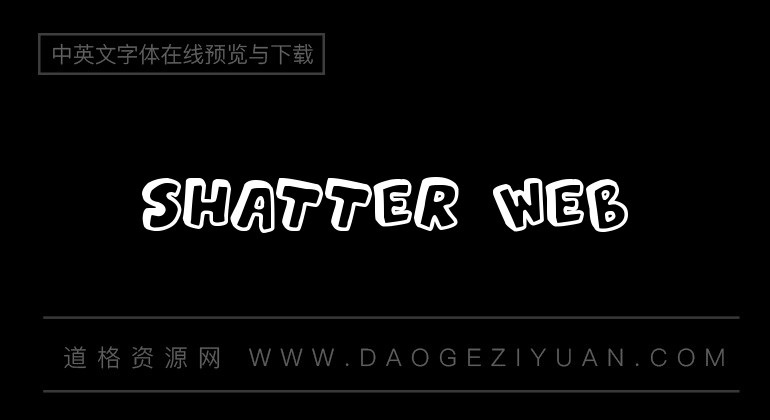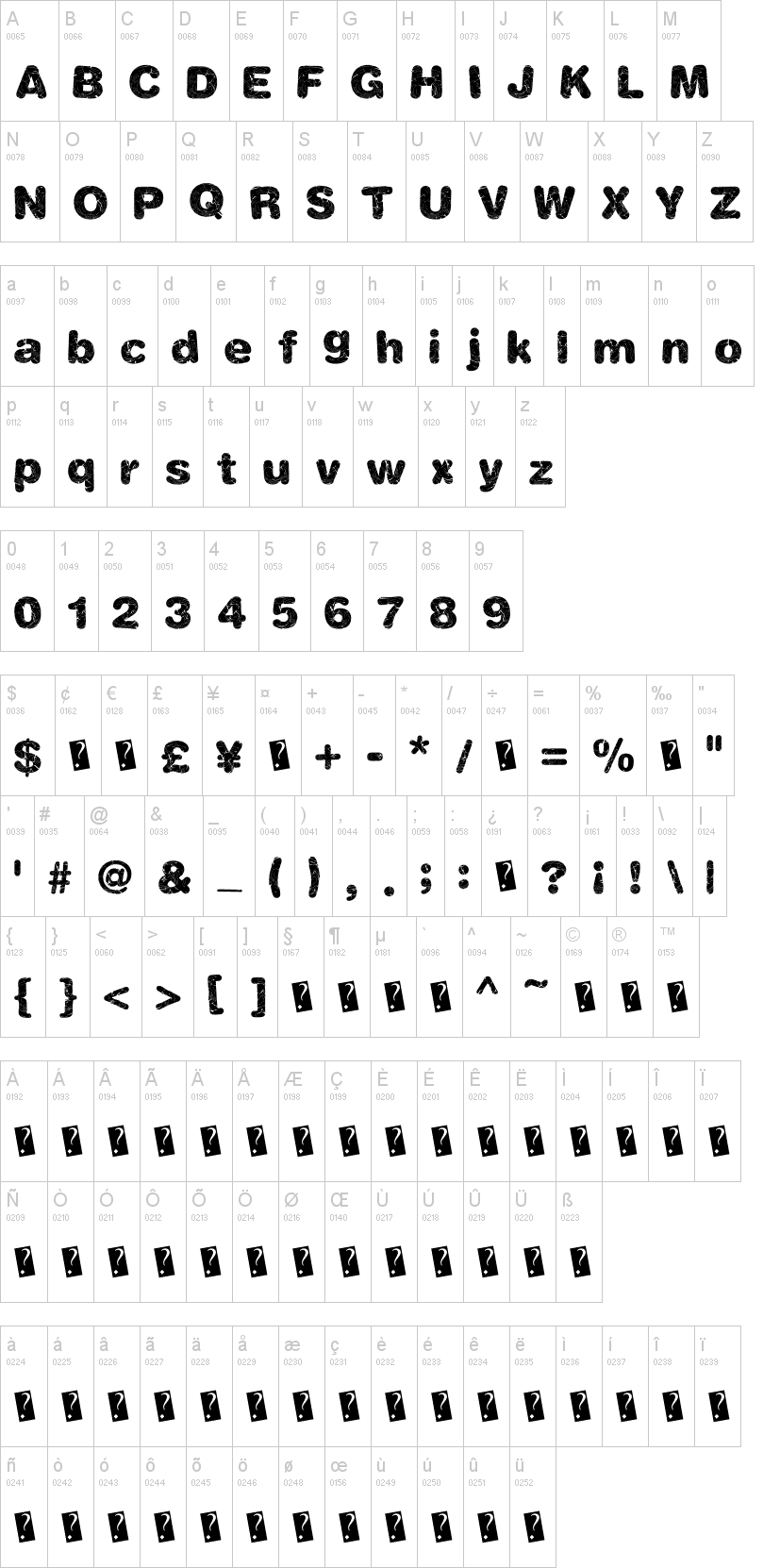
Shatter Web 是一种比较特殊的字体,它的特点在于每个字符都被分割成了许多小块,就像是被破碎的玻璃一样。这种字体看起来十分独特和醒目,适合用于一些需要突出效果的设计中,比如海报、广告等。 Shatter Web 字体的设计风格比较独特,但也存在一些缺点。由于每个字符都被分割成了很多小块,所以它在小字号下不太易读,而且也不太适合用于长篇文字排版。此外,由于它的设计比较复杂,所以在一些低分辨率的屏幕上显示可能会出现模糊或失真的情况。 总体来说,Shatter Web 字体适合用于一些需要醒目效果的设计中,但在其他情况下可能并不那么实用。内容介绍
Shatter Web是一款非常不错的手写艺术字体,具有很好的视觉感,适合于文化类的宣传设计、商业类品牌的广告和产品包装设计以及个性化文字排版等较多场景。